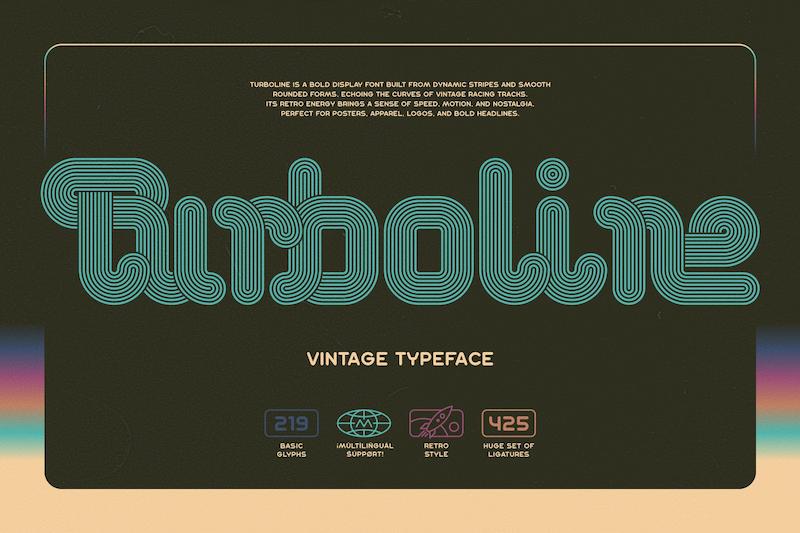
توربولاین، یک فونت دیسپلی بولد و توپُر است که از نوارهای پویا و اشکال گرد و نرم ساخته شده و منحنیهای پیستهای مسابقهای قدیمی را تداعی میکند. انرژی رتروی آن حس سرعت، حرکت و نوستالژی را به ارمغان میآورد و برای پوسترها، لوگوها و عناوین برجسته کاملاً مناسب است.
برای دستیابی به یک جلوهٔ یکپارچه، فونت توربولاین مجموعهٔ عظیمی از لیگچرها را دارد. لطفاً مطمئن شوید که ویژگی "استاندارد لیگاچرز" (Standard Ligatures) اوپنتایپ در برنامهٔ شما فعال است. فونت توربولاین از بیشتر زبانهای اروپایی پشتیبانی میکند. برای مشاهدهٔ مجموعهٔ کامل کاراکترهای موجود، لطفاً به تصاویر (اسکرینشاتها) مراجعه کنید.
طبقهبندی: دکوراتیو
فاصلهگذاری: نرمال
اندازه بهینه: بزرگ (دیسپلی، پوستر)